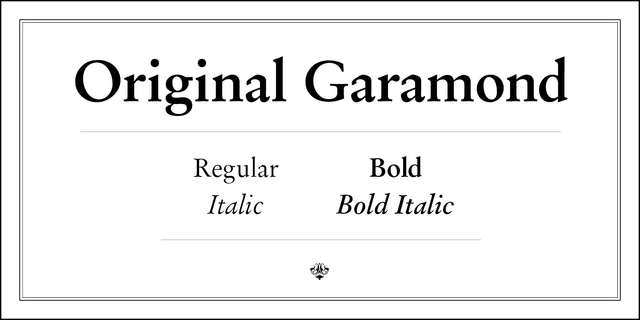
Немецкая фирма D. Stempel AG разработала эту версию шрифта Гарамон в 1925 году на основе рисунка шрифта французского пуансониста середины XVI века Клода Гарамона. Этот шрифт отличается от других версий Гарамона своей угловатостью. Он также слегка темнее по цвету, чем другие Гарамоны, и очень хорошо читается в текстовых кеглях. Может применяться для широкого спектра типографских работ. Original Garamond является версией шрифта Stempel Garamond фирмы Bitstream. Кириллические версии разработаны для фирмы ParaType в 2000 году (дизайнер Гаянэ Багдасарян).
вежливый, пафосный, благородный, изящный, красивый, аккуратный, уважительный, прилежный, тактичный, образцовый, традиционный, классический, художественный, серебристый, образованный, мастерский, исторический, гуманитарный, динамичный, умный, комильфо
библиотека, искусство, музей, литература, эстетика, проза, поэзия, музыка, симфония, вино, образование, живопись, концерт, комильфо, финансы Стилистика: